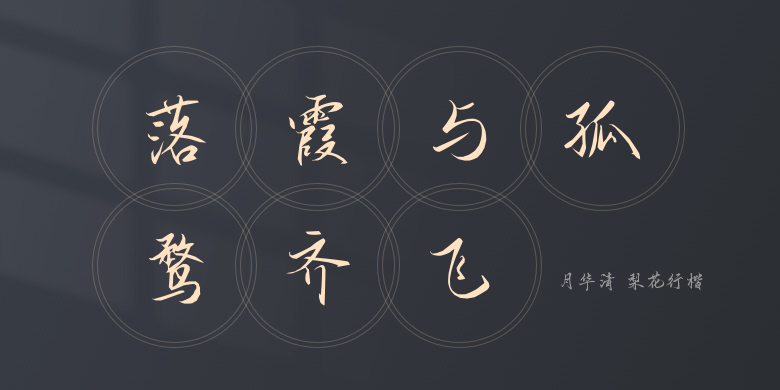
月华清 梨花行楷
月华清 梨花行楷,这款字体结构工整、笔画清晰,兼顾美观与易读性,适用于标题、正文、海报、包装、LOGO 等多种场景。字形优雅稳定,风格百搭耐看,适配日常排版与创意设计,让文字呈现更舒适、更具质感。月华清 梨花行楷一笔一画,皆是细节,以均衡的比例、流畅的线条打造舒适视觉体验,字形端正大气,风格简约现代。无论是商业设计、品牌宣传还是日常排版,都能轻松驾驭,让文字更有格调与力量。月华清 梨花行楷字体下载。